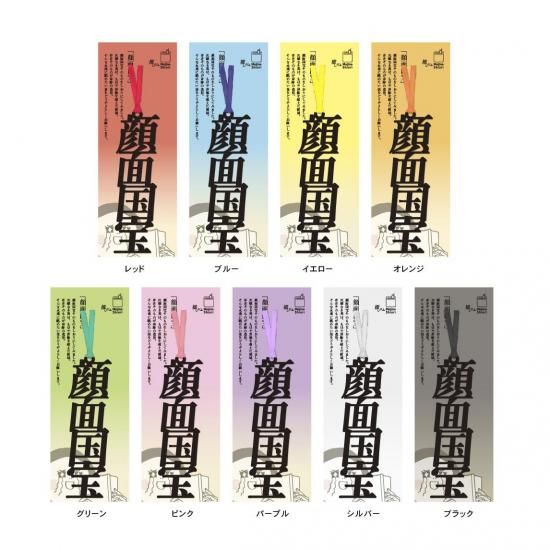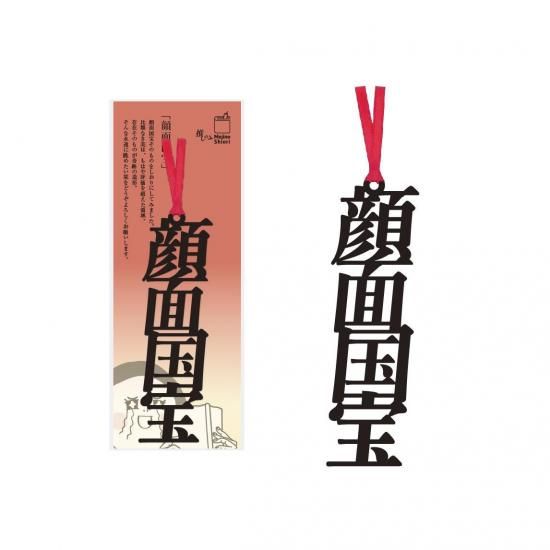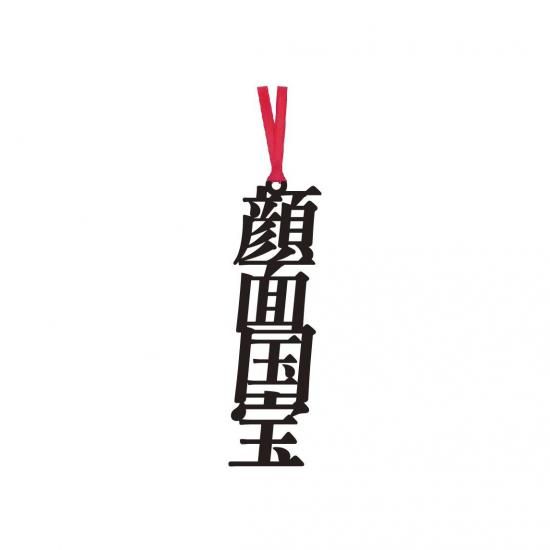
文字の推しのしおり「顔面国宝」【推しカラーが9色から選べます!】
顔面国宝そのものをしおりにしてみました。
比類なき美は、もはや評価を超えた領域。
存在そのものが奇跡の造形。
そんな永遠に眺めたい栞をどうぞよろしくお願いします。
木材パルプや綿を原料とした環境素材を採用し、耐久性・耐水性に優れたファイバーの特徴を活かすことで、言葉がフォントごと切り取られたような巧緻で美しい『文字のしおり』のデザインが実現しています。